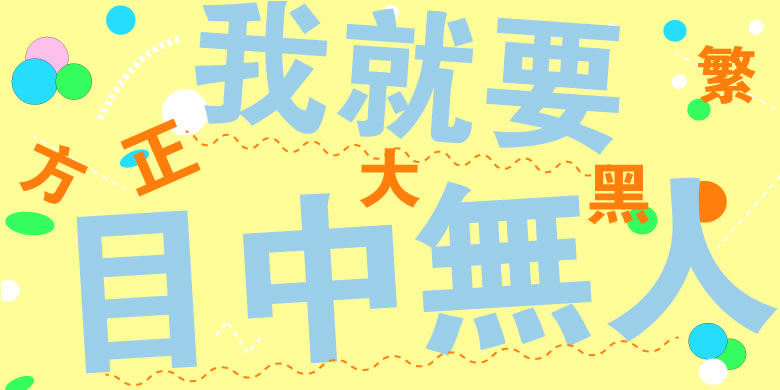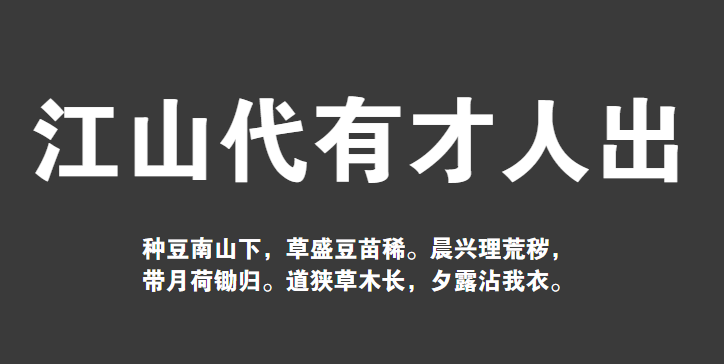
品牌:方正字库设计师:方正字模部发行时间:2000字库编码:大陆简体(GB2312-80)、大陆繁体(GB12345-90)、简繁扩展(GBK)、港台地区(BIG-5)分类:黑体
方正大黑源自1971年上海字模一厂设计的行头黑,字形结构延续了铅字时代的黑体风格。这款字体的中宫紧凑,横竖笔画的两端没有喇叭口,竖和撇的起笔留有细微的饰角,笔画粗壮有力。方正大黑的整体风格中庸平和,具有明显的时代特征,适用于报刊、杂志和书籍中的大型标题。
字体分类:黑体